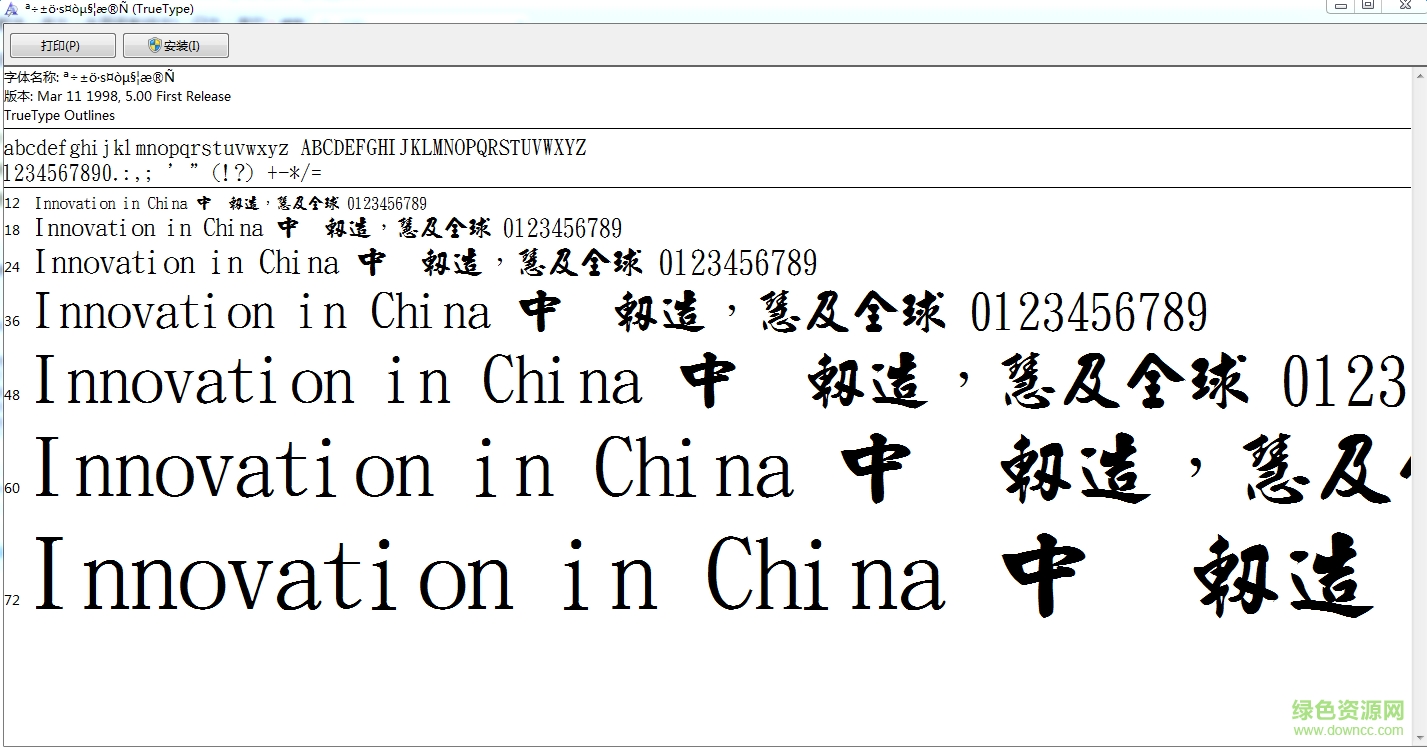
軟件介紹 軟件標(biāo)簽: 金梅新毛筆行書 金梅字體 金梅新毛筆行書繁體字體是一款極受歡迎的金梅字體,字體俊逸灑脫,美觀又實用,小編為大家打包整理好了,下載解壓即可使用!需要的小伙伴快來綠色資源網(wǎng)下載吧!字體安裝說明方法一:控制面板/字體/文件/安裝新字體;方法二:直接將字體復(fù)制到C:\WINDOWS\Fonts。方法三:針對win7系統(tǒng),用戶只需選中字體右鍵安裝即可。注意事項本站所有字體資源僅供個人學(xué)習(xí)與參考,如需商業(yè)使用請到相關(guān)官網(wǎng)授權(quán)。 軟件截圖 上一張下一張(1 / 1) 安裝詳細(xì)截圖 猜你喜歡 行書字體 毛筆字體 行書字體 行書字體包括了鋼筆字行書字體大全、硬筆行書字體等,是一種介于楷書和草書之間的字體。為什么這樣說?因為行書字體既有草書的流暢感,又有楷書的端正感,可以說,行書結(jié)合了草書和楷書的特點(diǎn),形成了獨(dú)特好看的行書字體。喜歡的朋友,趕快下載體驗吧! 查看更多>> 繁體行書字體 9.76M/中文/4.0/免費(fèi)版下載 winman tun10011字體 17.57M/中文/6.6/下載 南構(gòu)嘉飛行書字體 10.00M/中文/6.6/下載 c g流麗行書體繁/簡 4.39M/中文/5.0/下載 北方行書簡體 2.63M/中文/7.2/下載 qxyingbixing 1.26M/中文/8.0/下載 毛筆字體 毛筆字體是一類同硬筆書法完全不同的書寫方式,毛筆方法種類繁多更顯飄逸與古典氣質(zhì),是中國人的經(jīng)典傳承,無論是用于對聯(lián)、藝術(shù)設(shè)計還是門匾都顯示深沉莊重,綠色資源網(wǎng)小編整理了毛筆書法字體大全,歡迎大家下載體驗! 查看更多>> plume毛筆字體 416KB/中文/10.0/下載 衡山毛筆行書 4.16M/中文/10.0/下載 金梅新毛筆草楷 3.41M/中文/10.0/下載 金梅新毛筆隸書 2.34M/中文/10.0/下載 味わい毛筆pro字體 35.00M/中文/6.0/下載 葉根友毛筆行書2.0版 1.09M/中文/1.7/免費(fèi)版下載 其他版本下載 標(biāo)題 大小 更新日期 下載 下載地址 電腦版 金梅新毛筆行書字體 點(diǎn)擊報錯 軟件無法下載或下載后無法使用,請點(diǎn)擊報錯,謝謝! 關(guān)閉報錯反饋 請描述您所遇到的錯誤,我們將盡快予以修正,謝謝! *必填項,請輸入內(nèi)容 本類最新 金梅海報美工體 金梅新箭頭字范例字體 免費(fèi)版 金梅特黑水花字形字體 免費(fèi)版 金梅粗尖頭字范例繁體字體 免費(fèi)版 金梅淡古字ttf 免費(fèi)版 金梅浪漫鏡射體 用戶評論 熱門評論 最新評論 發(fā)表評論 查看所有評論(0) 昵稱: 請不要評論無意義或臟話,我們所有評論會有人工審核. 字?jǐn)?shù): 0/500 (您的評論需要經(jīng)過審核才能顯示)